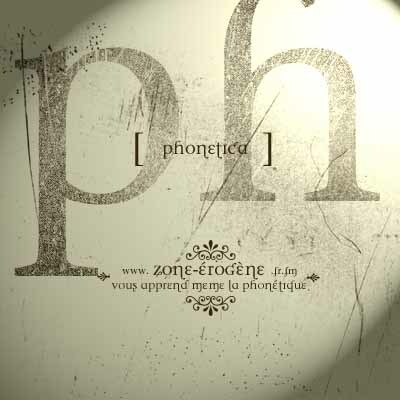
Phonetica von Dasklem Inc. ist eine kostenlose Serifenschrift für Display-Anwendungen mit einer literarischen, leicht eigenwilligen Note. Die Buchstaben verbinden klassischen typografischen Kontrast mit unerwarteten Schwüngen und Haken. Das Ergebnis ist eine Schrift, die irgendwo zwischen formellem Editorial-Design und einem ausdrucksstarken, charaktervollen Serif-Stil angesiedelt ist.
Damit eignet sie sich hervorragend für Magazin-Köpfe, Album-Cover, Filmplakate, edle Verpackungen und kurze Buchtitel – überall dort, wo eine kostenlose Schrift kultiviertes Drama braucht, ohne dabei zu verspielt zu wirken. Auch für Monogramme oder initialbasiertes Branding ist sie eine exzellente Wahl, da die zulaufenden Striche und geschwungenen Details selbst kurzen Wörtern eine markante Silhouette verleihen.